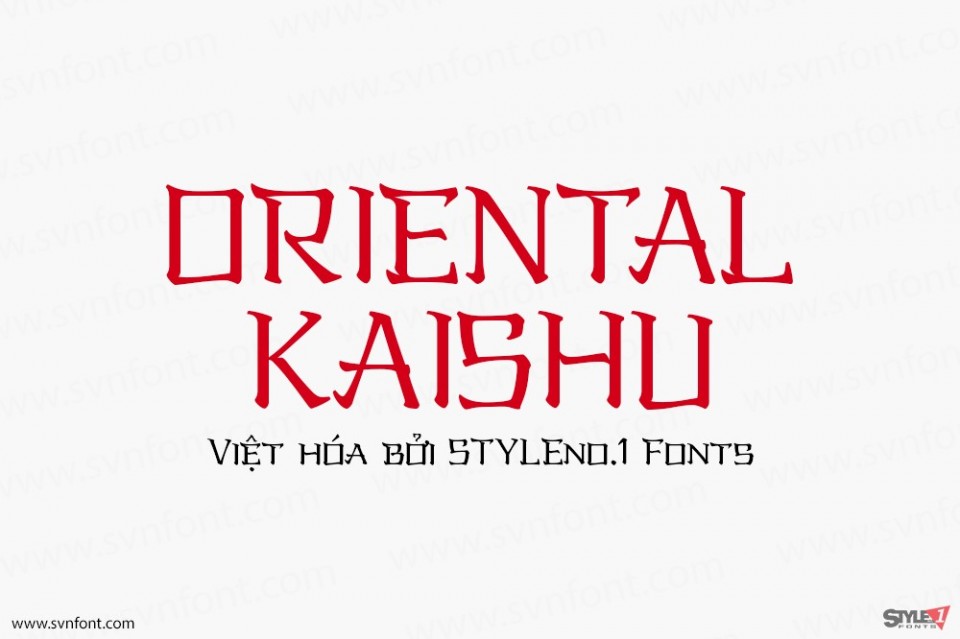
Giới thiệu về Font việt hóa SVN Oriental Kaishu style nhật bản
Trong thế giới thiết kế đồ họa hiện nay, việc tìm kiếm một Font Chữ mang đậm hơi thở văn hóa Đông Á là điều vô cùng cần thiết. Font việt hóa SVN Oriental Kaishu style nhật bản là một tác phẩm typography độc đáo, tái hiện hoàn hảo những đường nét uyển chuyển của thư pháp truyền thống Nhật Bản. Với cấu trúc bút pháp Kaishu (Khải thư) rõ ràng, bộ font này không chỉ mang lại vẻ đẹp cổ điển mà còn giữ được sự trang trọng, tinh tế trong từng nét chữ. Phiên bản việt hóa giúp người dùng tại Việt Nam dễ dàng ứng dụng vào các dự án thiết kế mà không lo lỗi font hay thiếu dấu tiếng Việt.
Đặc điểm nổi bật của Font việt hóa SVN Oriental Kaishu style nhật bản
Phong cách thư pháp ấn tượng
Đặc trưng lớn nhất của Font việt hóa SVN Oriental Kaishu style nhật bản chính là sự mô phỏng những nét cọ mực tàu đầy nội lực. Mỗi ký tự đều được chăm chút kỹ lưỡng, tạo cảm giác như được viết tay trực tiếp trên giấy washi. Điều này giúp bộ chữ trở nên sống động, có hồn và tạo ấn tượng mạnh mẽ với người xem ngay từ cái nhìn đầu tiên.
Tính ứng dụng linh hoạt trong thiết kế
Bộ font này cực kỳ phù hợp cho các dự án liên quan đến văn hóa, ẩm thực hoặc trang trí nghệ thuật. Bạn có thể sử dụng nó để làm menu nhà hàng Nhật, thiết kế bìa sách, poster phim cổ trang hoặc các ấn phẩm quảng bá du lịch. Sự kết hợp giữa nét chữ đậm nhạt đan xen giúp tạo nên sự cân bằng hoàn hảo giữa truyền thống và hiện đại.
Kết luận và trải nghiệm bộ chữ độc đáo